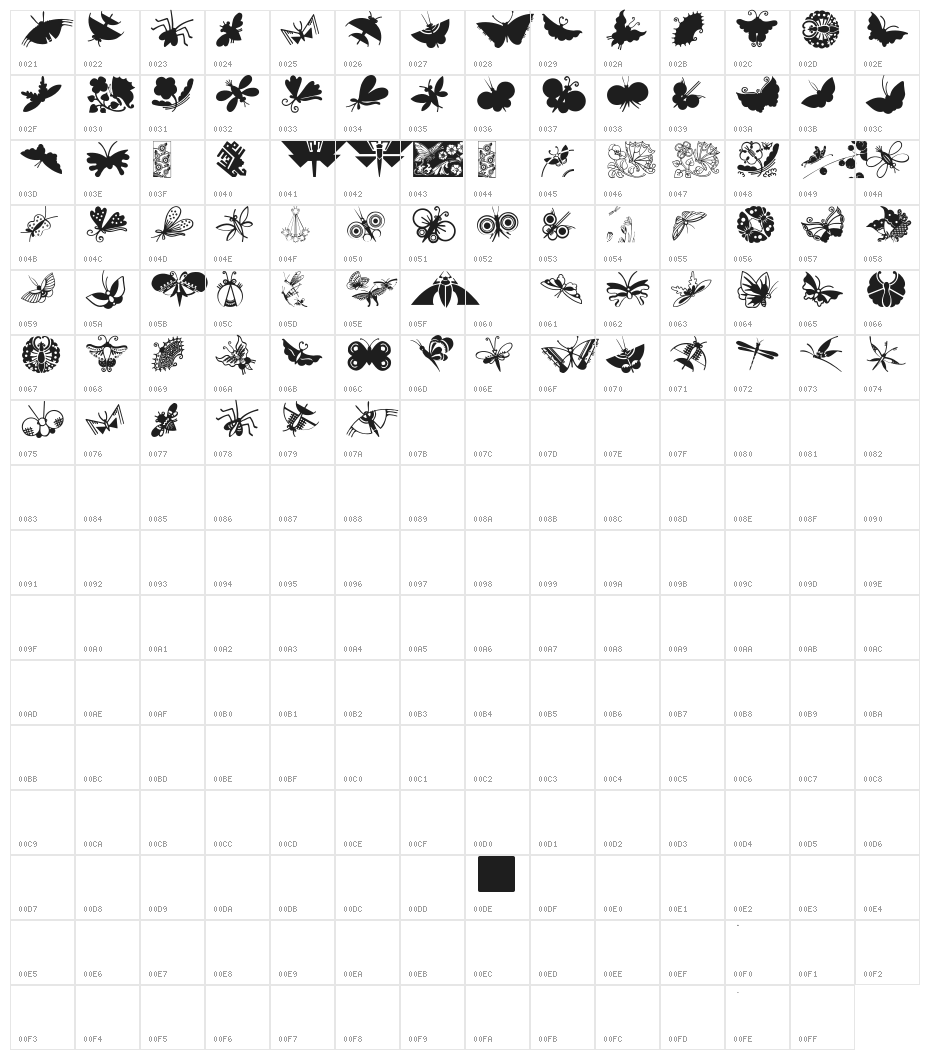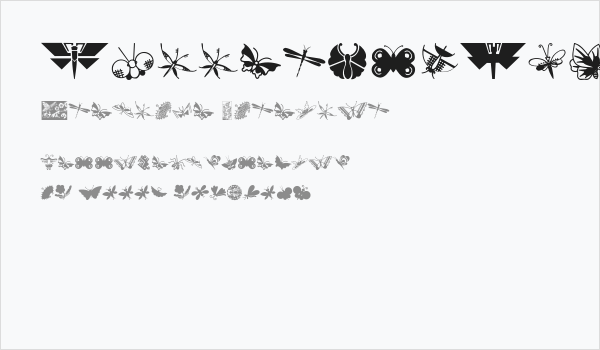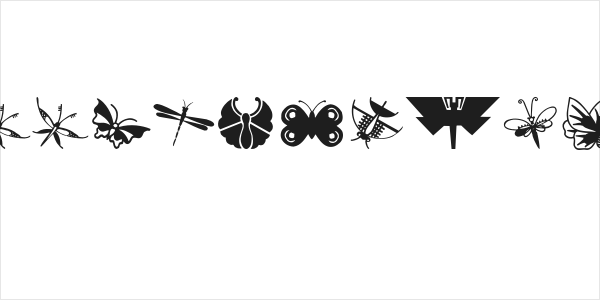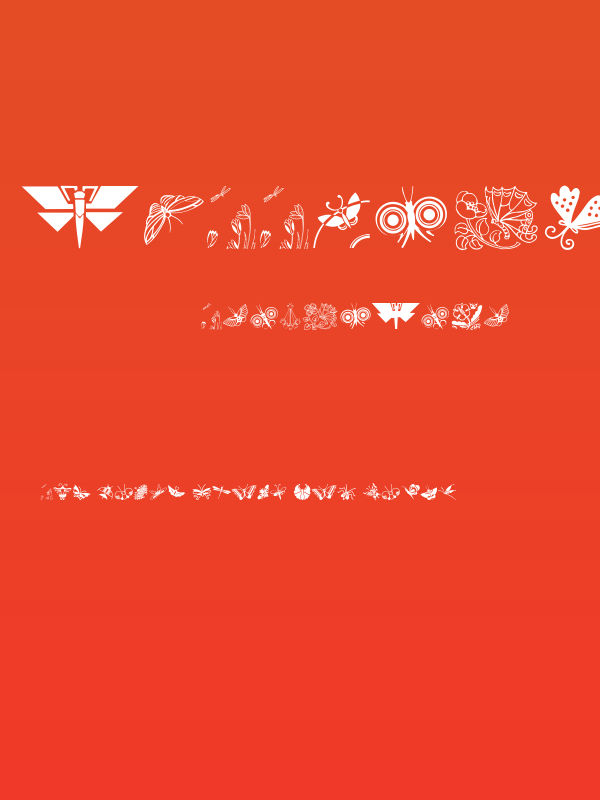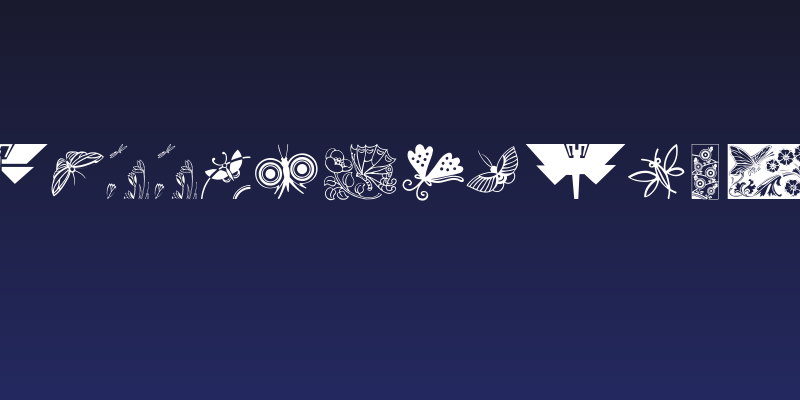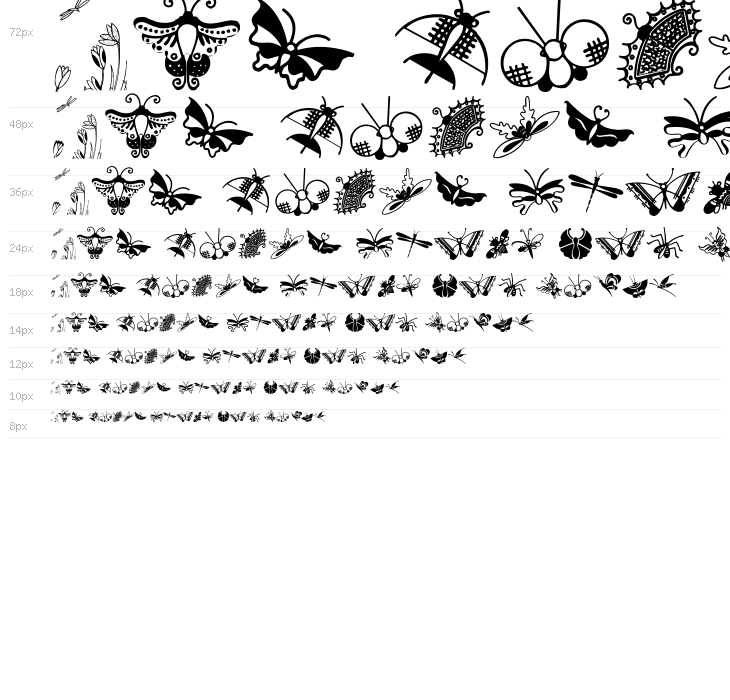
ButterflyAndCo Font
✎ Dingbats
| Gesamtstil | Decorative, Whimsical, Nature-inspired |
| Anwendungsfall | Decorative elements, Logos, Craft projects, Themed headings |
| Vorgeschlagene Projekte | Invitations, scrapbooking, greeting cards, nature-themed branding, decorative borders, children’s projects, and craft designs. |